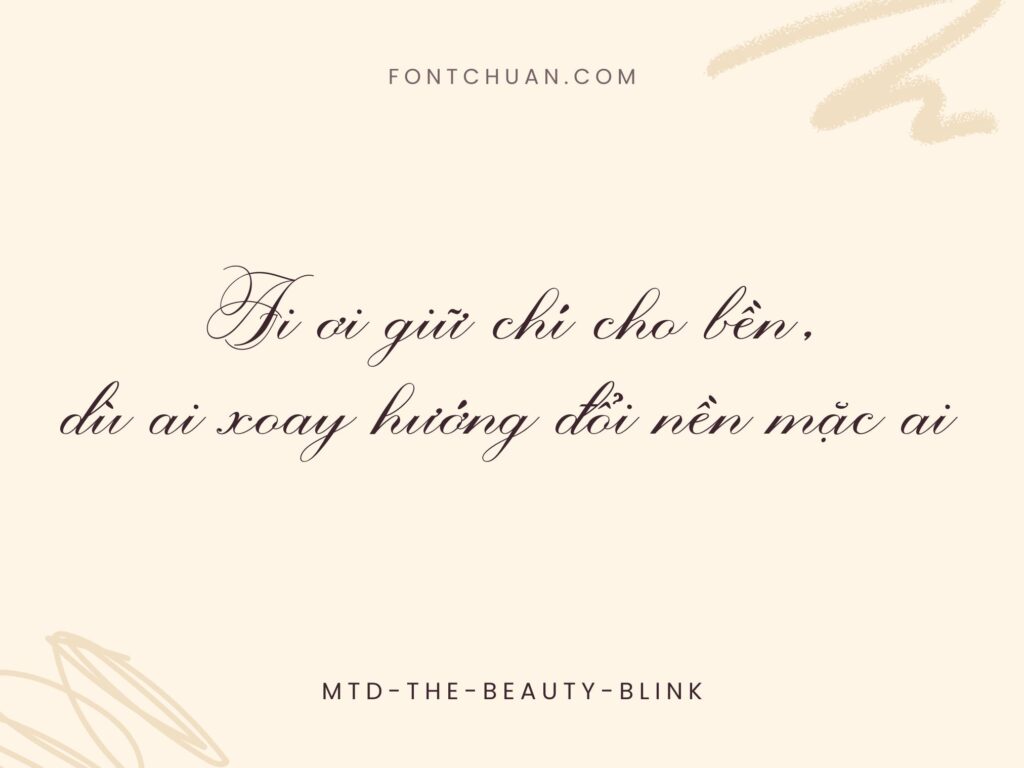
Font MTD The Beauty Blink Việt Hóa
Font MTD The Beauty Blink là một kiểu chữ viết tay thanh lịch, được thiết kế bởi Soft Creative và đã được Việt hóa bởi Mộc Hạ. Font này hỗ trợ đầy đủ tiếng Việt cùng hơn 90 ngôn ngữ khác, mở rộng khả năng ứng dụng trong các thiết kế đa ngôn ngữ. Đây là một trong những phông chữ được cộng đồng thiết kế đánh giá cao và sử dụng trong nhiều dự án sáng tạo, đáp ứng nhu cầu đa dạng của người dùng.
MTD The Beauty Blink nổi bật với các đường nét mềm mại và uyển chuyển, tạo cảm giác tự nhiên và nghệ thuật. Font rất phù hợp cho các thiết kế logo, tiêu đề, bao bì sản phẩm, thiệp mời và các ấn phẩm đòi hỏi sự tinh tế và độc đáo. Các ngành nghề phù hợp bao gồm quảng cáo, giáo dục, công nghệ, thiệp cưới và ảnh cưới. Font này cũng lý tưởng cho các sự kiện như Tết, Giáng sinh, Valentine và các lễ hội khác.